康熙字典と日本の漢字への影響
漢字のかたちと意味を定めた、漢字文化の基準書
康熙字典(こうきじてん)は、清の康熙帝の勅命で編纂された大規模な漢字字典であり、東アジアの文字文化に大きな影響を与えました。本記事では、康熙字典の成立と特徴、そして日本の漢字運用・辞書編纂・教育・出版に及ぼした影響を整理します。
康熙字典とは
康熙字典(こうきじてん)は、中国清代の第4代皇帝である康熙帝の勅命によって編纂された、国家事業としての大規模漢字字典です。1716年(康熙55年)に完成しました。全体で約12年をかけて成立したこの字典は、当時までに存在した膨大な字書・韻書・経典注釈を集成し、漢字文化圏における字音・字義・用例を明記の基準を示しました。
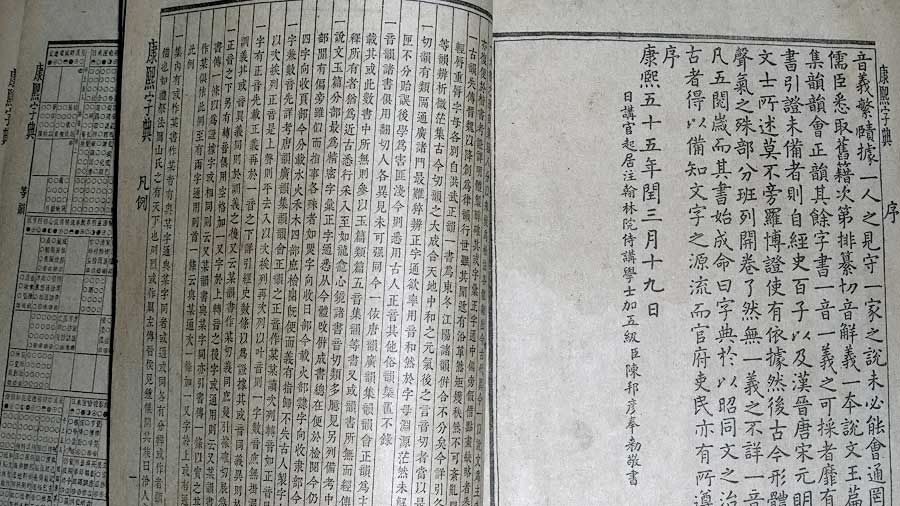
編纂の背景には、清朝による統治体制の安定と、文化的権威の確立という政治的意図があります。康熙帝は学問を重視した皇帝として知られ、儒学・漢学の整理と統一を国家的課題と捉えていました。その一環として、漢字の字形・字義を整理し、学術的にも実務的にも信頼できる標準字典を整備する必要がありました。
実際の編纂作業には、陳廷敬を総裁官とする学者官僚が動員され、明代以前の字書や韻書、古典籍、金石文資料などが広範に参照されました。その結果、収録字数は約4万7千字に及び、部首配列・画数順という体系的構成を備えた、当時としては前例のない規模と完成度を誇る字典が誕生しました。
このように康熙字典は、単なる辞書ではなく、「国家が定めた漢字の正統的整理結果」としての性格を持ち、その権威性と網羅性によって、中国のみならず日本・朝鮮・ベトナムなど、広く漢字文化圏全体に長期的な影響を及ぼすことになりました。
康熙字典の特徴
最大の特徴は、部首による分類と、部首内を画数で整理する索引性です。字形だけでなく、字義・用例・典拠を挙げることで、単なる「字の一覧」ではなく、伝統注釈学の参照点として機能しました。とりわけ、漢字を分類する部首の数を214に整理したことは有名で、この「康熙214部首」は現在の Unicode に収録される部首(Kangxi Radicals)にもそのまま受け継がれています。
- 部首体系
- 後世の辞書や索引で繰り返し参照される基準となり、日本の字書にも影響。
- 字形の提示
- 特定の字形(いわゆる「康熙字典体」)が、印刷・写本・後代字書で事実上の規範として扱われる契機になる。
- 典拠主義
- 古典籍に基づく語義・用例の提示が、学術的な権威を支え、日本の漢学にも受容される。
日本への伝来と受容の背景
日本では古くから中国の字書が輸入・受容されてきましたが、近世以降の漢学の隆盛と出版文化の発達により、権威ある字典としての康熙字典が参照されやすい環境が整いました。漢文読解、校訂、書写、出版の現場で「拠り所となる字形・字義」を求める需要が、受容を後押ししました。
日本の字書・国字辞典への影響
日本の辞書編纂では、中国字書の体系(部首・画数・典拠)を取り込みつつ、日本固有の訓読み・国字・用法を加える形で発展しました。康熙字典は、その「骨格」として参照されることが多く、見出しの立て方、異体字の扱い、典拠の示し方に影響を与えました。
- 見出し語の選定
- 字形の標準を決める際に参照されやすい。
- 異体字整理
- 同一字の揺れをどこまで許容するかの判断材料になる。
- 語義の枠組み
- 漢籍に基づく語義分類が、日本の字義説明にも波及する。
字体・字形の標準化と「康熙字典体」
日本の漢字は、手書き・木版本・活字・官庁文書など多様な媒体で字形が揺れます。そこで参照されやすかったのが、印刷を通じて広く流通した康熙字典の字形です。結果として「康熙字典体」と呼ばれる字形の傾向が、明朝体・宋体系フォントなどの設計思想にも影響し、出版現場のきれいな字形の感覚を形作る一因になりました。
部首法・索引文化への影響
日本で漢字を引く方法として、部首引きと総画数は長く基本手段でした。康熙字典の部首体系は、後代の辞書・索引でも踏襲されやすく、学習者が「部首→画数→字形」という手順で探索する習慣を強化しました。
- 学習上の利点
- 形から引けるため、読みが不明でも探索できる。
- 学習上の難点
- 部首判定が難しい字や、部首の歴史的揺れがある字で迷いやすい。
教育・出版・活字文化への波及
江戸期から近代にかけて、教育(寺子屋・藩校・私塾)と出版(版本・活版)が拡大する中で、字形の参照元が必要になりました。康熙字典は、漢籍の校訂や学術的引用だけでなく、印刷物の字形を整える「規範」としても影響を与え、結果として日本の活字文化における字体の安定に寄与しました。
近代以降の当用漢字・常用漢字との関係
近代日本では、行政・教育の効率化のために使用漢字の範囲や字体(いわゆる新字体)が整理されました。この動きは康熙字典の体系とは目的が異なりますが、実務では「伝統的字体(旧字体)を確認する参照先」として、康熙字典的な字形が引き続き意識されました。つまり、近代の標準化は簡略化・統制の方向へ、康熙字典は伝統的正字の参照へと役割分担が生まれたと言えます。
フォント・Unicode・辞書データなど現代の実務への影響
現代では、文字はデジタル環境で扱われ、Unicodeやフォント実装が字形の見え方を左右します。ここでも康熙字典に由来する字形観は間接的に残っており、特に「伝統的な字形(旧字体・康熙系の形)」と「日本の標準字体(新字体・通用字体)」の差異が、組版や校正、固有名詞の表記で問題になります。
- 人名・地名
- 戸籍・登記・史料に基づく字形確認が必要になる。
- 外字対応
- 辞書的典拠として伝統字形が参照されることがある。
- フォント差
- 同じコードポイントでもフォント設計思想で字形が異なる。
まとめ:康熙字典が日本の漢字に残したもの
康熙字典は、日本の漢字文化に対して「字形・字義の権威ある参照点」「部首・画数による検索体系」「出版・活字文化における規範意識」をもたらしました。
一方で、近代以降の日本は教育・行政の要請から標準字体や使用漢字を整理し、康熙字典的世界観とは異なる方向へも進みました。それでも、古典読解、校訂、固有名詞、異体字整理といった場面で、康熙字典の影響は今も参照される伝統として息づいています。